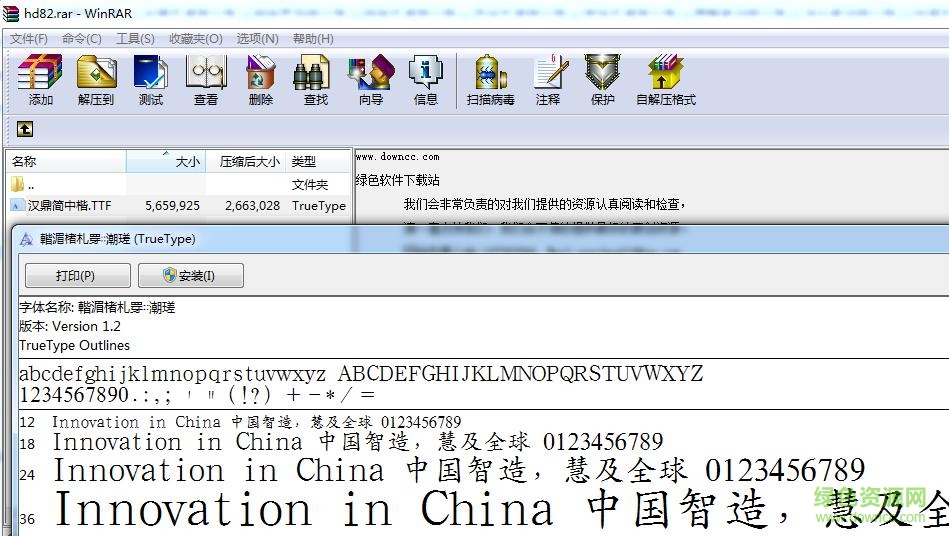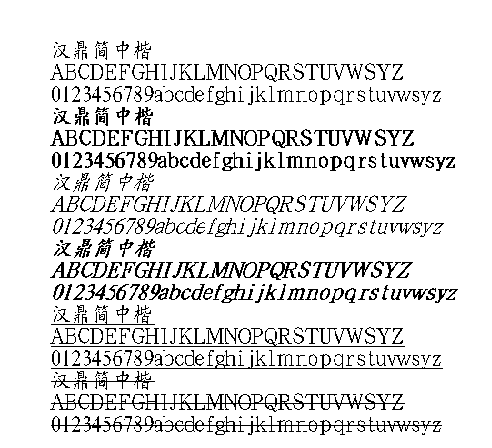
漢鼎中楷簡體字體
漢鼎簡中楷字體是一款漢鼎字體系列的楷體字體文件,讓你能夠完成各類word文檔編輯,與藝術(shù)字創(chuàng)作等功能,讓你能夠運用到生活與工作當(dāng)中,發(fā)揮重要的作用!
特色介紹
漢鼎簡中楷是漢鼎字體庫中一種字體,常用于美工設(shè)計方面,喜歡的朋友不要錯過。
漢鼎簡中楷